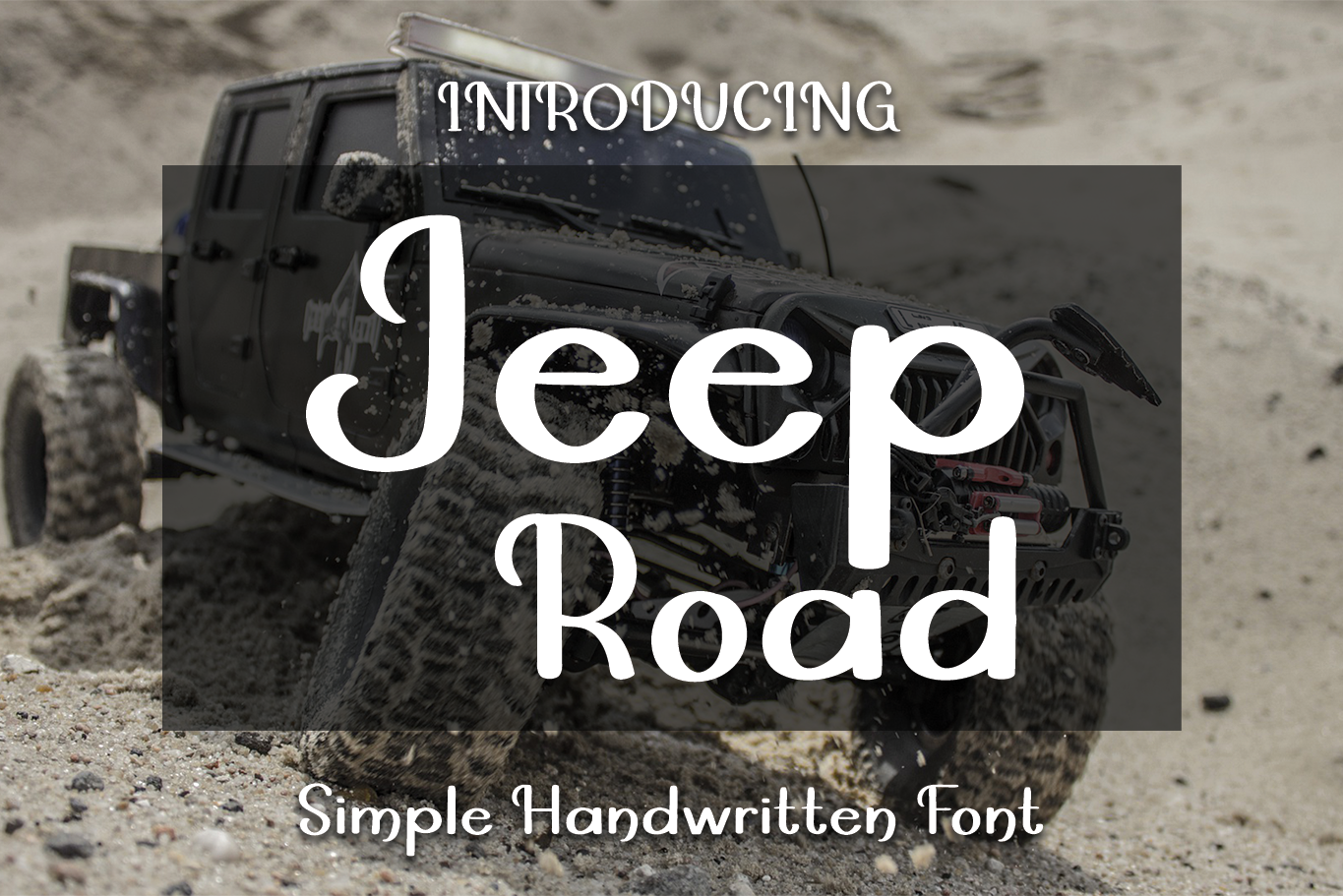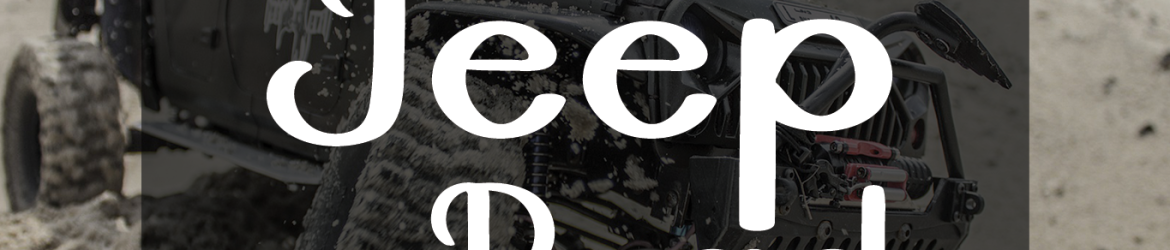
Jeep Road Font – Download Grátis
A fonte ‘Jeep Road Font’ é uma escolha perfeita para designers buscando expressar naturalidade e adaptabilidade em seus projetos. Desenhada por el hotcig, essa script font simplesmente não decepciona. Suas linhas levemente torturadas evocam um estilo que é autêntico e único, oferecendo uma versatilidade impressionante para diversos tipos de design. Seu valor principal reside em sua capacidade de se adaptar a uma variedade extensa de ambientes gráficos, desde letras corporativas até elementos ilustrativos e arte digital. O designer chama atenção para o fato de que o limite único é apenas imaginativo, incentivando os criadores a explorarem o máximo das possibilidades apresentadas por esta fonte. Ideal tanto para personalizar logotipos quanto para adicionar uma camada única à sua arte digital, ‘Jeep Road Font’ é uma opção versátil que pode se adaptar facilmente a qualquer tipo de projeto.